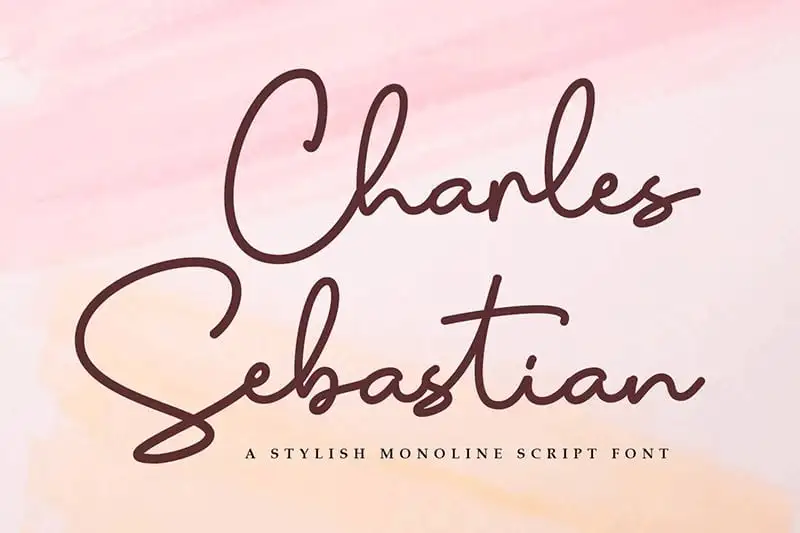
Charles Sebastian Handwritten Font – Fonte Grátis
Charles Sebastian Handwritten Font
A Charles Sebastian Handwritten Font é uma elegante tipografia feita à mão, perfeita para criar declarações estilizadas e sofisticadas, ou para adicionar uma dose de classe aos seus designs. Este tipo de letra feita à mão não apenas traz um ar suave e relajado a qualquer projeto, mas também oferece uma maneira refinada de destacar seu trabalho. Seja você criando um layout sofisticado para revistas ou desenvolvendo um design minimalista para sua próxima camiseta, a Charles Sebastian Handwritten Font é uma opção perfeita para adicionar personalidade e delicadeza aos seus materiais. Se procura algo que seja um pouco mais pessoal e autêntico em seu próximo projeto visual, esta fonte pode ser o elemento que você está procurando. Com sua aparência aconchegante e fluida, ela é perfeita para anúncios de marca, letras de sites, ou até mesmo como uma maneira única de expressar seu estilo pessoal no design gráfico. Com 99designs como seu designer, você pode garantir que o resultado final seja realmente único, oferecendo uma fonte impecável que vai deixá-lo se sentindo em casa e atraente ao mesmo tempo.